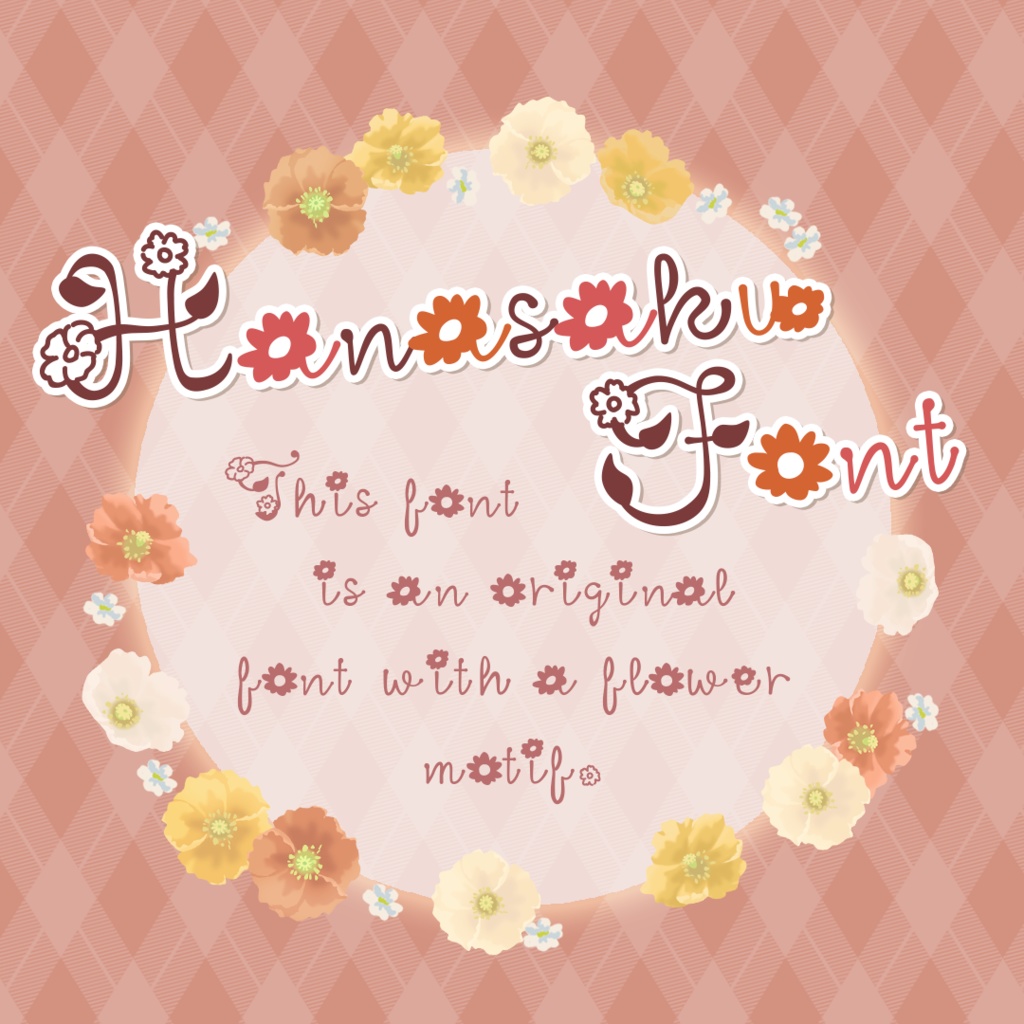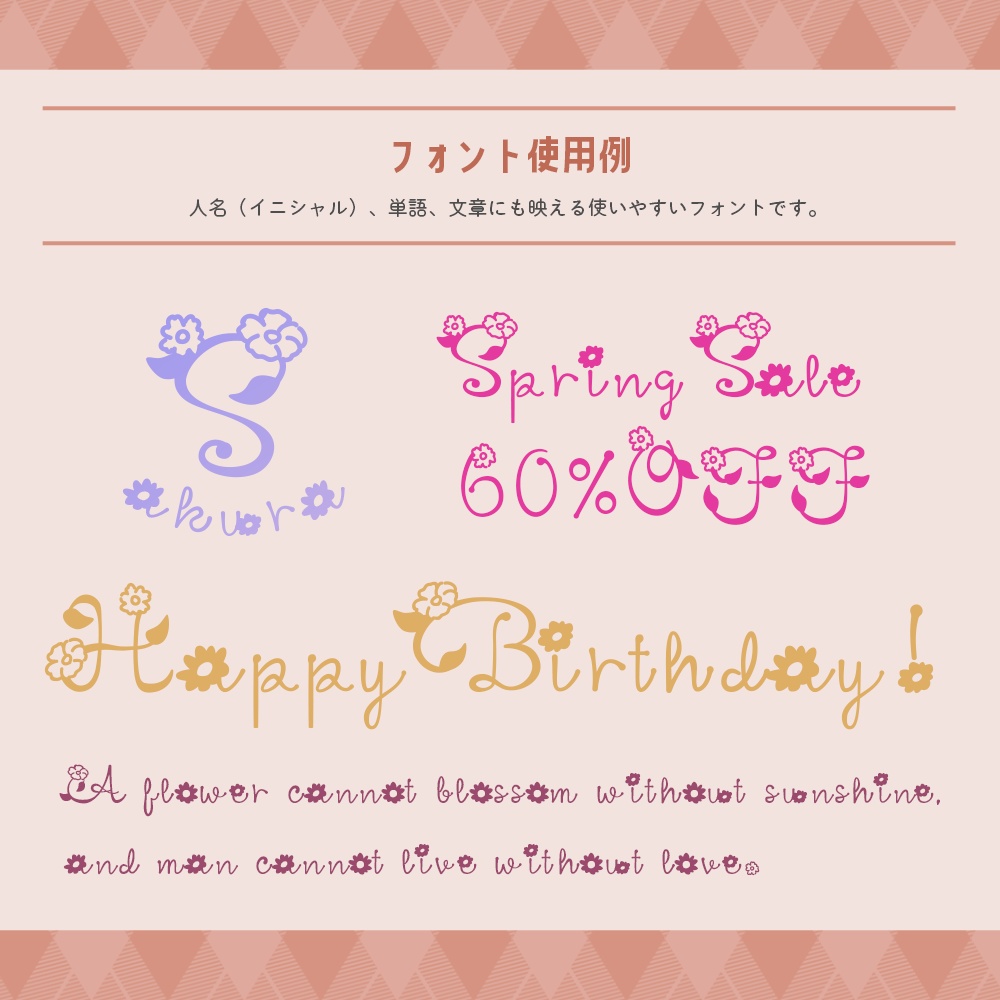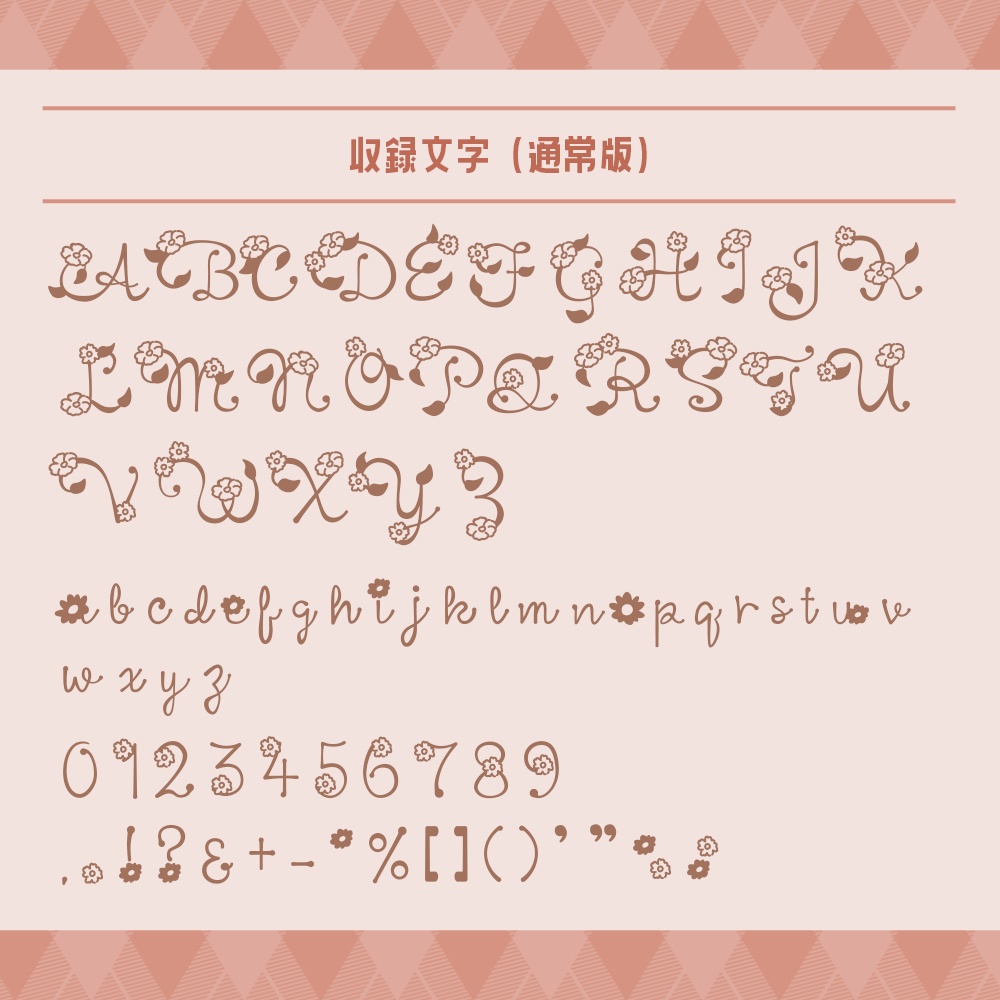
フリー有》お花フォントHanasakuFont:文字を打つと花が咲く🌼
お花モチーフのオリジナルフォント「HanasakuFont」(はなさくフォント)です。 ガーリーデザインや記念日やお祝い事などにもピッタリなフォントです。 アルファベット大文字、小文字の子音、数字・記号の一部にお花の装飾がついています。文字を打つと程よくお花が咲く感じがとてもかわいいです。